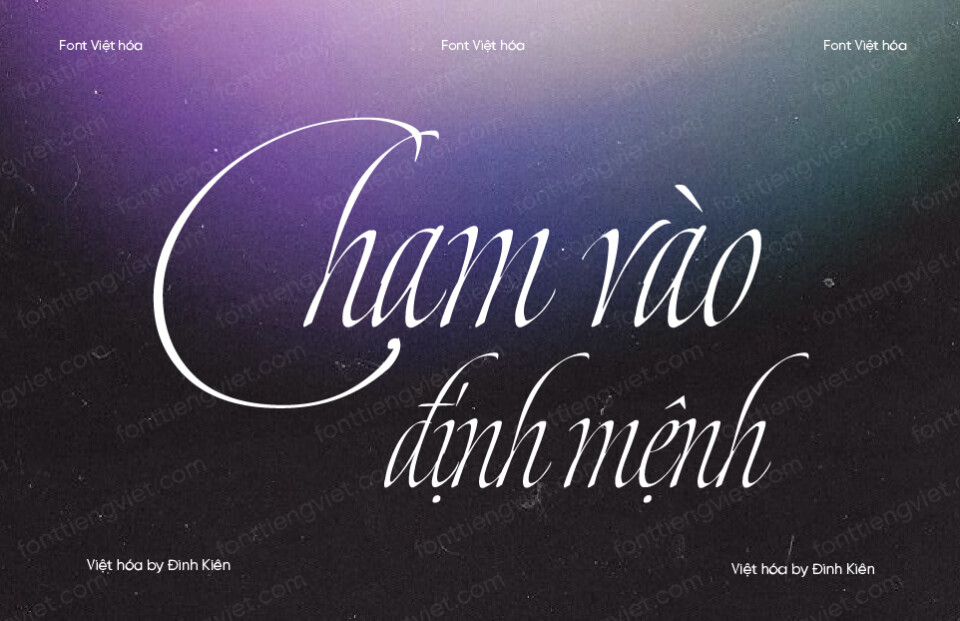
Trong thế giới thiết kế đồ họa số, việc lựa chọn một Font Chữ phù hợp có thể tạo nên sự khác biệt lớn, biến một tác phẩm bình thường thành một kiệt tác ấn tượng. Đối với những nhà thiết kế chuyên nghiệp cũng như những người yêu thích sáng tạo tại Việt Nam, nhu cầu về các font chữ đẹp, độc đáo và đặc biệt là đã được Việt hóa luôn rất cao. Một trong những lựa chọn nổi bật đang thu hút sự chú ý rộng rãi chính là Font Việt hóa UTM Dream Script Pro. Đây không chỉ là một font chữ đơn thuần mà còn là một công cụ mạnh mẽ giúp bạn thể hiện cá tính và sự chuyên nghiệp trong mọi dự án.
Khám Phá Sức Hút Của Font Việt hóa UTM Dream Script Pro Trong Thiết Kế
Font Việt hóa UTM Dream Script Pro nổi bật với phong cách viết tay mềm mại, uyển chuyển nhưng không kém phần sang trọng và hiện đại. Sự kết hợp giữa nét truyền thống của chữ viết tay và sự tinh tế trong từng đường nét đã tạo nên một font chữ có khả năng biến hóa đa dạng. Từ những thiệp mời cưới lãng mạn, logo thương hiệu tinh xảo, cho đến các ấn phẩm truyền thông yêu cầu sự mềm mại và cá tính, font chữ này đều có thể đáp ứng một cách xuất sắc. Đặc biệt, việc đã được Việt hóa hoàn chỉnh là một điểm cộng cực lớn, đảm bảo font chữ hiển thị đầy đủ và chính xác tất cả các ký tự tiếng Việt có dấu, không còn tình trạng lỗi font hay thiếu ký tự gây khó chịu.
Ưu Điểm Nổi Bật Của UTM Dream Script Pro Được Việt Hóa
- Tính Thẩm Mỹ Cao: Với các nét chữ mượt mà, bay bổng, font này mang lại cảm giác nhẹ nhàng, thanh lịch và rất nghệ thuật. Đây là lựa chọn lý tưởng cho các dự án cần sự tinh tế và nữ tính.
- Việt Hóa Hoàn Chỉnh: Mọi ký tự tiếng Việt, từ dấu sắc, huyền, hỏi, ngã, nặng cho đến các chữ cái đặc biệt như “ă”, “â”, “ô”, “ơ”, “ư”, “đ” đều được hỗ trợ đầy đủ và hiển thị chuẩn xác, giúp người dùng an tâm khi sáng tạo nội dung tiếng Việt.
- Đa Dạng Ứng Dụng: Phù hợp cho nhiều mục đích khác nhau như thiết kế thiệp mời, banner quảng cáo, bao bì sản phẩm, logo, tiêu đề sách, tạp chí, hay thậm chí là các bài thuyết trình yêu cầu tính nghệ thuật.
- Dễ Dàng Kết Hợp: UTM Dream Script Pro có thể dễ dàng phối hợp với các font chữ serif hoặc sans-serif khác để tạo ra sự cân bằng và hài hòa trong bố cục tổng thể của thiết kế.
Việc sử dụng một font chữ chất lượng như UTM Dream Script Pro không chỉ giúp nâng cao giá trị thẩm mỹ của sản phẩm thiết kế mà còn thể hiện sự chuyên nghiệp và tỉ mỉ của người thiết kế. Font chữ này mang đến một luồng gió mới cho các dự án, giúp chúng trở nên độc đáo và thu hút hơn trong mắt người xem. Đặc biệt trong bối cảnh thị trường thiết kế ngày càng cạnh tranh, việc sở hữu những công cụ độc đáo và hiệu quả là chìa khóa để tạo ra sự khác biệt.
Ứng Dụng Thực Tiễn Của Font UTM Dream Script Pro Trong Đời Sống
Không chỉ dừng lại ở các dự án thiết kế chuyên nghiệp, Font Việt hóa UTM Dream Script Pro còn có thể được ứng dụng rộng rãi trong đời sống hàng ngày của học sinh, sinh viên và giáo viên. Chẳng hạn, các bạn học sinh có thể sử dụng font này để thiết kế bìa báo tường, làm slide thuyết trình nhóm với phong cách độc đáo, hoặc tạo ra những tấm thiệp chúc mừng bạn bè, thầy cô nhân dịp đặc biệt. Đối với sinh viên, font có thể được dùng để làm tiêu đề luận văn, đồ án tốt nghiệp, hoặc các ấn phẩm sự kiện của trường, câu lạc bộ, giúp bài trình bày của bạn trở nên nổi bật và thu hút hơn.
Ngay cả trong các kỳ thi tốt nghiệp quan trọng, dù không trực tiếp sử dụng font để viết bài, nhưng việc luyện tập thiết kế các tài liệu ôn tập, ghi chú cá nhân với font chữ đẹp mắt có thể gián tiếp tạo cảm hứng học tập và giúp việc ghi nhớ trở nên thú vị hơn. Các giáo viên cũng có thể sử dụng font này để thiết kế các tài liệu giảng dạy, bài kiểm tra, hoặc các biểu ngữ trang trí lớp học, mang đến một không gian học tập thân thiện và sáng tạo hơn cho học sinh của mình.
Với sự linh hoạt và tính thẩm mỹ cao, UTM Dream Script Pro thực sự là một tài sản quý giá cho bất kỳ ai muốn truyền tải thông điệp một cách nghệ thuật và hiệu quả. Nó giúp các sản phẩm thiết kế không chỉ đẹp mắt mà còn chứa đựng cảm xúc, cá tính riêng biệt.
Tóm lại, Font Việt hóa UTM Dream Script Pro là một lựa chọn tuyệt vời cho những ai đang tìm kiếm một Font Chữ viết tay độc đáo, thanh lịch và đã được tối ưu hóa hoàn toàn cho tiếng Việt. Với những ưu điểm vượt trội về mặt thẩm mỹ và tính năng, font chữ này chắc chắn sẽ là một trợ thủ đắc lực, mở ra không gian sáng tạo không giới hạn cho mọi dự án của bạn. Dù bạn là một nhà thiết kế đồ họa chuyên nghiệp, một học sinh đang chuẩn bị cho kỳ thi tốt nghiệp, hay đơn giản là người yêu thích cái đẹp, UTM Dream Script Pro đều xứng đáng có mặt trong bộ sưu tập font của bạn để mang lại những giá trị thẩm mỹ và ứng dụng cao nhất. Hãy trải nghiệm và cảm nhận sự khác biệt mà font chữ này mang lại!